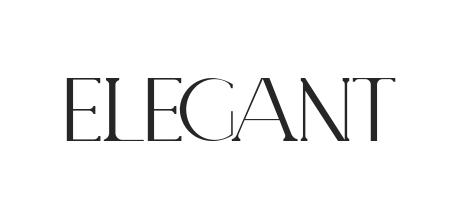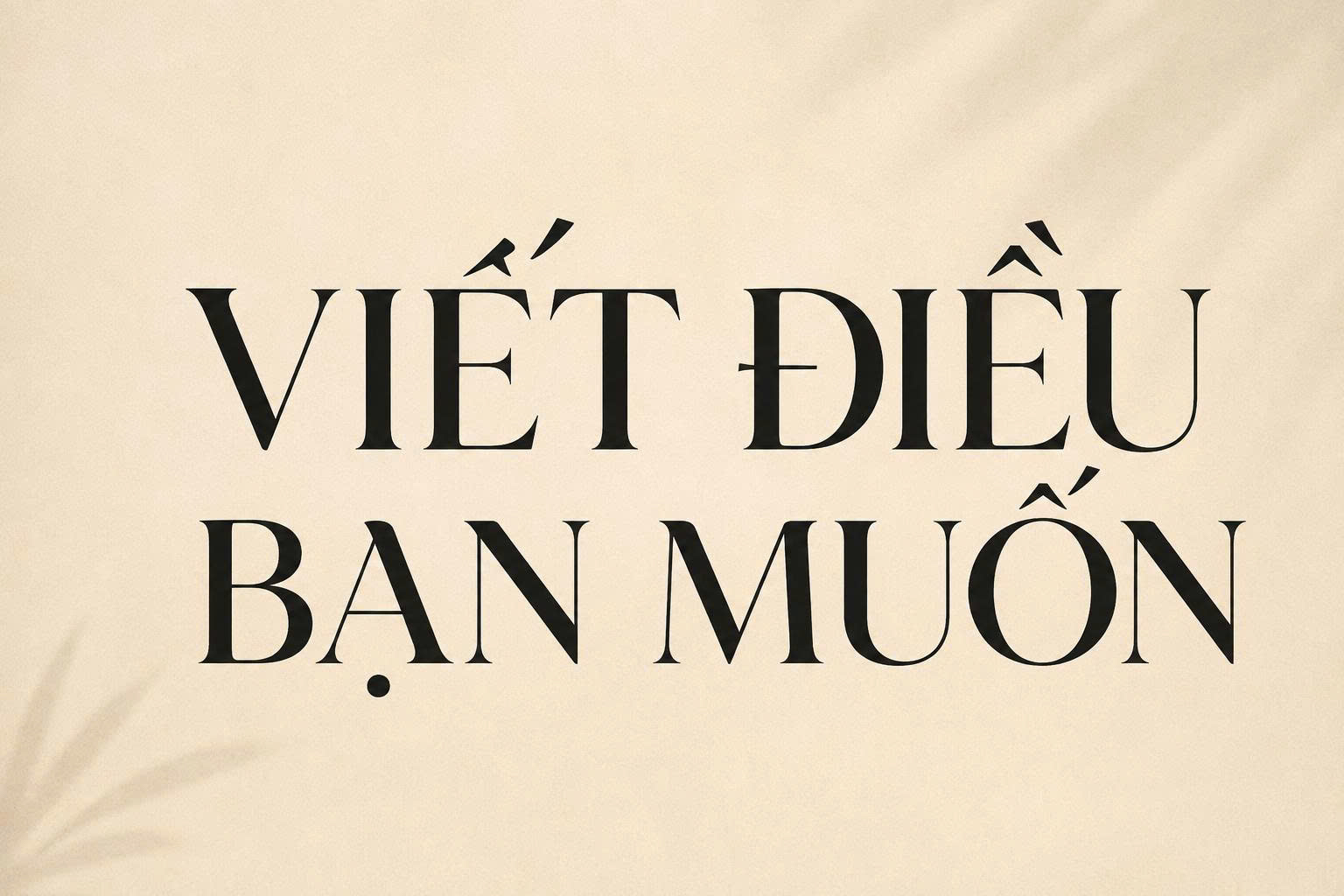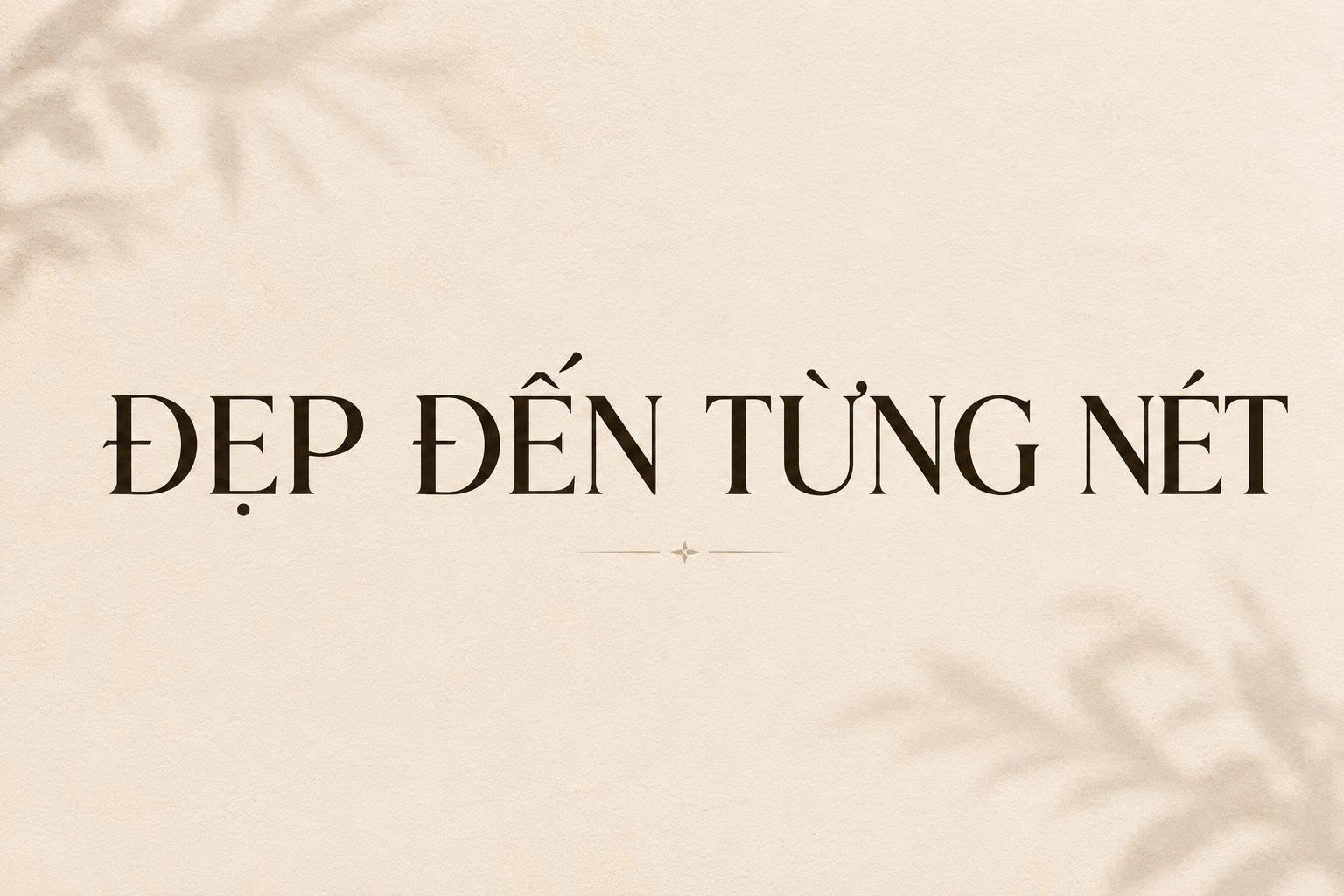
Font Elegant Việt hóa là nhóm phông chữ thuộc dòng Luxury Display Serif mang đậm dấu ấn của phong cách thiết kế châu Âu đương đại, nổi bật với sự tương phản mượt mà giữa các nét đứng dày dặn và đường chân chữ vuốt mảnh như sợi tơ. Với phong thái kiêu kỳ, đài các và đậm chất thẩm mỹ thời trang, font Elegant Việt hóa free là chất liệu trực quan tuyệt vời để các kiến trúc sư, nhà thiết kế nâng tầm không gian cho các bản vẽ phối cảnh biệt thự nghỉ dưỡng, sảnh đón tiếp khách sạn boutique hay bìa hồ sơ năng lực dự án.
Tỷ lệ đài các và độ tương phản duyên dáng của font Elegant Việt hóa
Điểm cuốn hút của font Elegant Việt hóa nằm ở cấu trúc hình thể thanh thoát với các đường cong chuyển tiếp mềm mại, loại bỏ cảm giác khô cứng của các kiểu chữ đồ họa công nghiệp thông thường. Các con chữ sở hữu tỷ lệ hình học chuẩn mực, các góc chân chữ được mài nhọn tinh tế mang lại cảm giác đĩnh đạc và uy nghiêm cho từng dòng tiêu đề.
Sự ổn định về mặt thị giác của dòng font này giúp khẳng định vị thế, sự tinh tế và gu thẩm mỹ sắc bén của đơn vị chủ trì dự án. Khi xuất hiện trên các bề mặt vật liệu kiến trúc hiện đại như đá cẩm thạch trắng vân mây, inox mạ vàng xước mờ, kính phản quang hay gỗ óc chó trong các căn nhà lắp ghép cao cấp, Elegant tạo nên điểm nhấn thị giác cuốn hút.
| Phân loại phong cách | Luxury Serif / Editorial Display / High-contrast |
| Nhóm phông tiêu biểu | Higuen Elegant Serif, DNV Elegant, Elegant Display |
| Mục đích phù hợp | Biển tên villa cao cấp, bìa hồ sơ năng lực, logo |
Tư vấn từ chuyên viên: Font Elegant sở hữu các nét thanh mảnh và độ tương phản lớn. Để bản thiết kế đạt hiệu quả thẩm mỹ tốt, bạn nên sử dụng phông chữ này cho các tiêu đề chính, tên dự án hoặc câu khẩu hiệu ngắn ở kích thước lớn từ 18pt trở lên. Phần nội dung mô tả kỹ thuật chi tiết nên đi kèm một phông chữ không chân thanh mảnh hơn để người xem tiếp nhận thông tin dễ dàng.
03 Ứng dụng font Higuen Elegant Serif Việt hóa vào công trình thực tế
Nhờ vẻ ngoài quý phái và tính thẩm mỹ cao cấp, bộ phông chữ này mang lại giá trị thực tế lớn trong khâu tạo điểm nhấn cho các công trình hiện đại:
- Biển hiệu mặt tiền cho Villa và Boutique Homestay: Những nét chữ thanh lịch của font Higuen Elegant Serif Việt hóa rất ăn ý khi gia công chữ nổi bằng inox vàng gương hoặc khắc chìm trên đá hoa cương, giúp căn nhà lắp ghép toát lên vẻ đài các và thu hút sự chú ý của du khách.
- Bìa hồ sơ năng lực dự án kiến trúc: Sử dụng font Elegant Việt hóa cho tên dự án và tiêu đề các chương mục giúp hồ sơ trông như một ấn phẩm tạp chí danh giá, thể hiện gu thẩm mỹ tinh tế và năng lực của đơn vị kiến tạo.
- Hệ thống biển tên phòng và bảng chỉ dẫn nội khu: Phông chữ này khi in trên kính mờ hoặc kim loại phủ sơn tĩnh điện sẽ giúp không gian sảnh đón tiếp và hành lang toát lên chất nghệ thuật thanh lịch.
03 Lưu ý bố cục DNV Elegant Việt hóa free giữ trọn vẻ tinh xảo
Để khai thác hiệu quả vẻ đẹp của dòng font thời trang quý tộc này mà không làm ảnh hưởng đến khả năng đọc của bản vẽ, người thiết kế nên lưu tâm một số kinh nghiệm sau:
- Tránh sử dụng ở kích thước quá nhỏ: Do có các nét thanh mỏng manh, dòng font này hiển thị đẹp nhất ở kích thước chữ từ trung bình trở lên trong in ấn. Ở kích thước quá nhỏ, nét thanh có thể bị mờ nhòe do độ mịn của chất liệu giấy in.
- Nới rộng khoảng cách ký tự: Đối với các tiêu đề viết hoa toàn bộ trong bộ DNV Elegant Việt hóa free, việc kéo giãn nhẹ khoảng cách giữa các chữ cái sẽ làm tăng tính trang nghiêm, giúp bố cục thông thoáng và mang đậm phong thái kiến trúc đương đại.
- Bố trí nền màu đơn sắc tương phản: Phông chữ phát huy hiệu quả thị giác cao khi đặt trên các nền màu đơn sắc có chiều sâu như đen tuyền, trắng ngọc trai, xám than hoặc xanh rêu sẫm, giúp các đường nét sắc sảo của bộ chữ được tôn vinh rõ ràng.